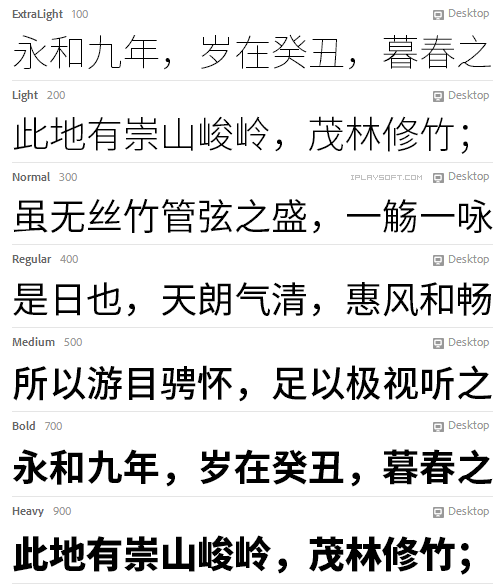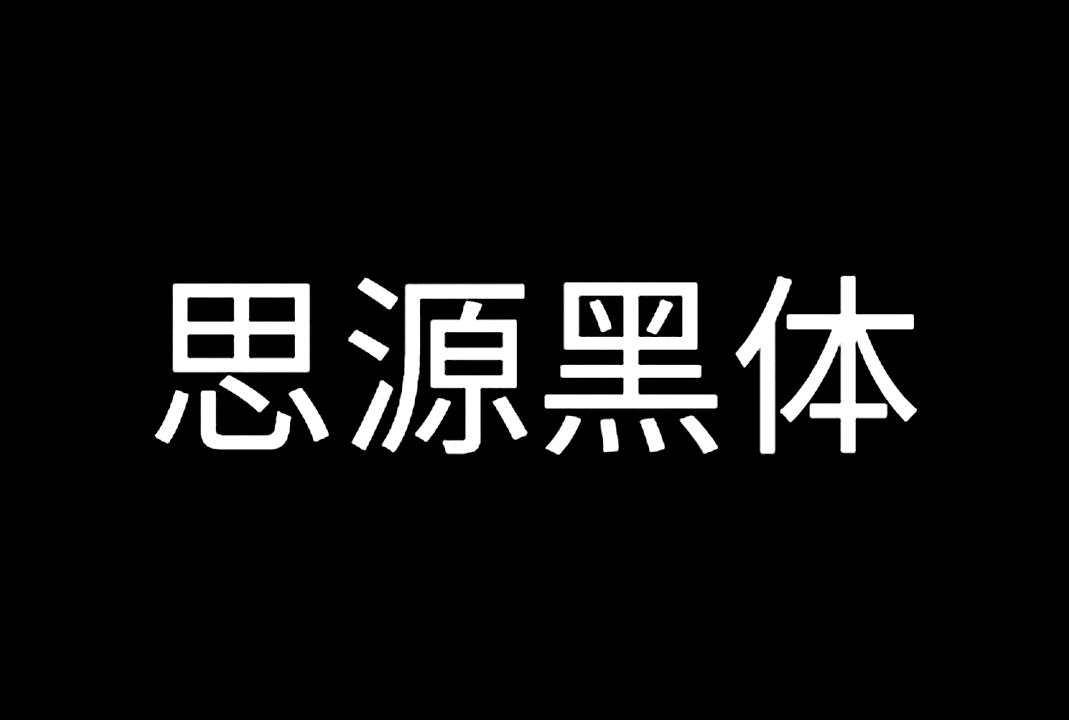
思源黑体是Adobe与Google历时三年在2014年7月宣布推出的一款开源字体,这是一款新的供桌面使用的开源 Pan-CJK 字体家族, 有七种字体粗细(ExtraLight、Light、Normal、Regular、Medium、Bold 和 Heavy),完全支持繁体中文、简体中文、日文和韩文,这些全部都包含在一种字体中。它还包括来自我们颇受欢迎的 Source Sans字体家族的拉丁文、希腊文和西里尔文字形。